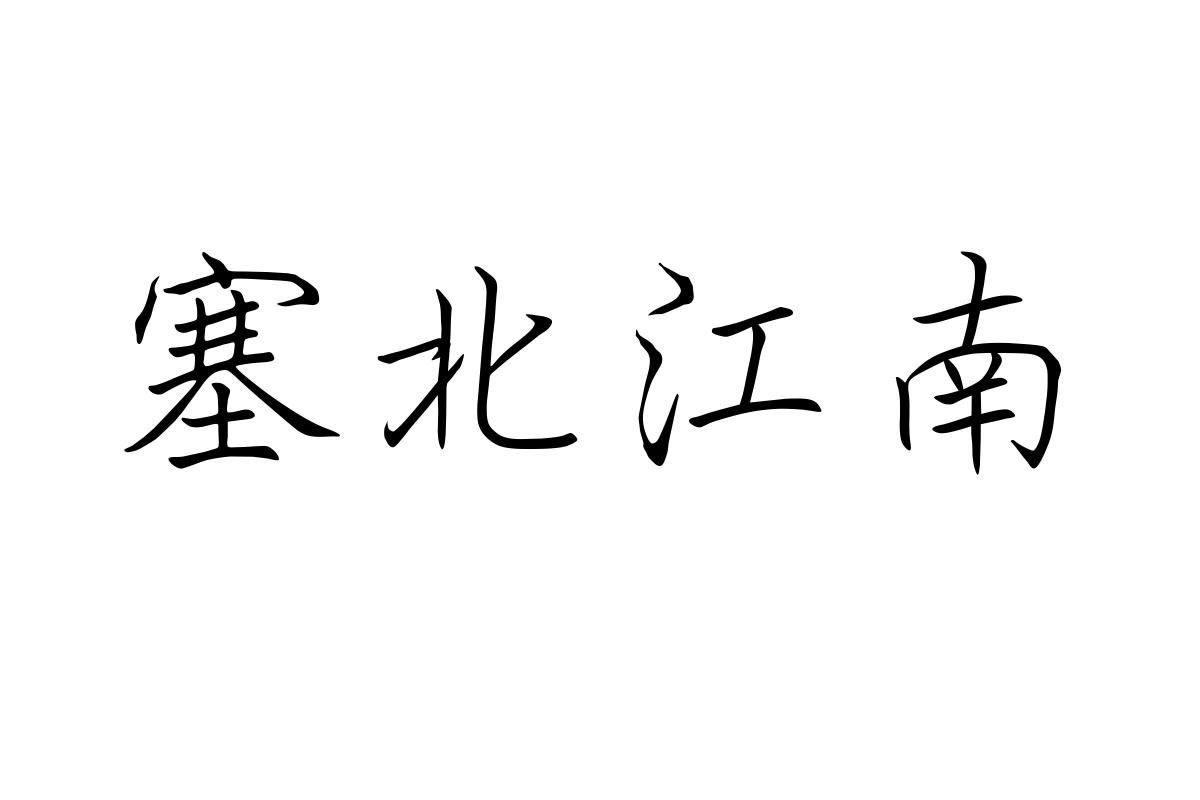
汉仪细行楷W是一套由汉仪公司开发的字体,主要用于书法和书写。这款字体的特点是笔画细腻,结构紧凑,适合用于书法和书写。它的线条流畅,笔锋清晰,给人一种优雅的感觉。同时,这款字体也适用于印刷,因为它的字形规整,易于排版。总的来说,汉仪细行楷W是一款非常实用的字体,无论是书法还是书写,都能展现出其独特的魅力。